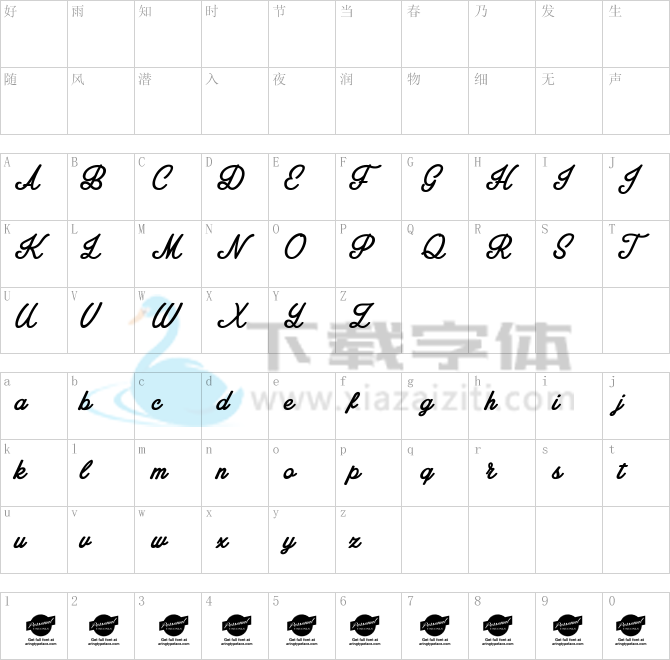
Amplify Personal Use Only.ttf字体下载
Amplify Personal Use Only.ttf字体下载,这款字体结构工整、笔画清晰,兼顾美观与易读性,适用于标题、正文、海报、包装、LOGO 等多种场景。字形优雅稳定,风格百搭耐看,适配日常排版与创意设计,让文字呈现更舒适、更具质感。Amplify Personal Use Only.ttf字体下载一笔一画,皆是细节,以均衡的比例、流畅的线条打造舒适视觉体验,字形端正大气,风格简约现代。无论是商业设计、品牌宣传还是日常排版,都能轻松驾驭,让文字更有格调与力量。Amplify Personal Use Only.ttf字体下载字体下载。